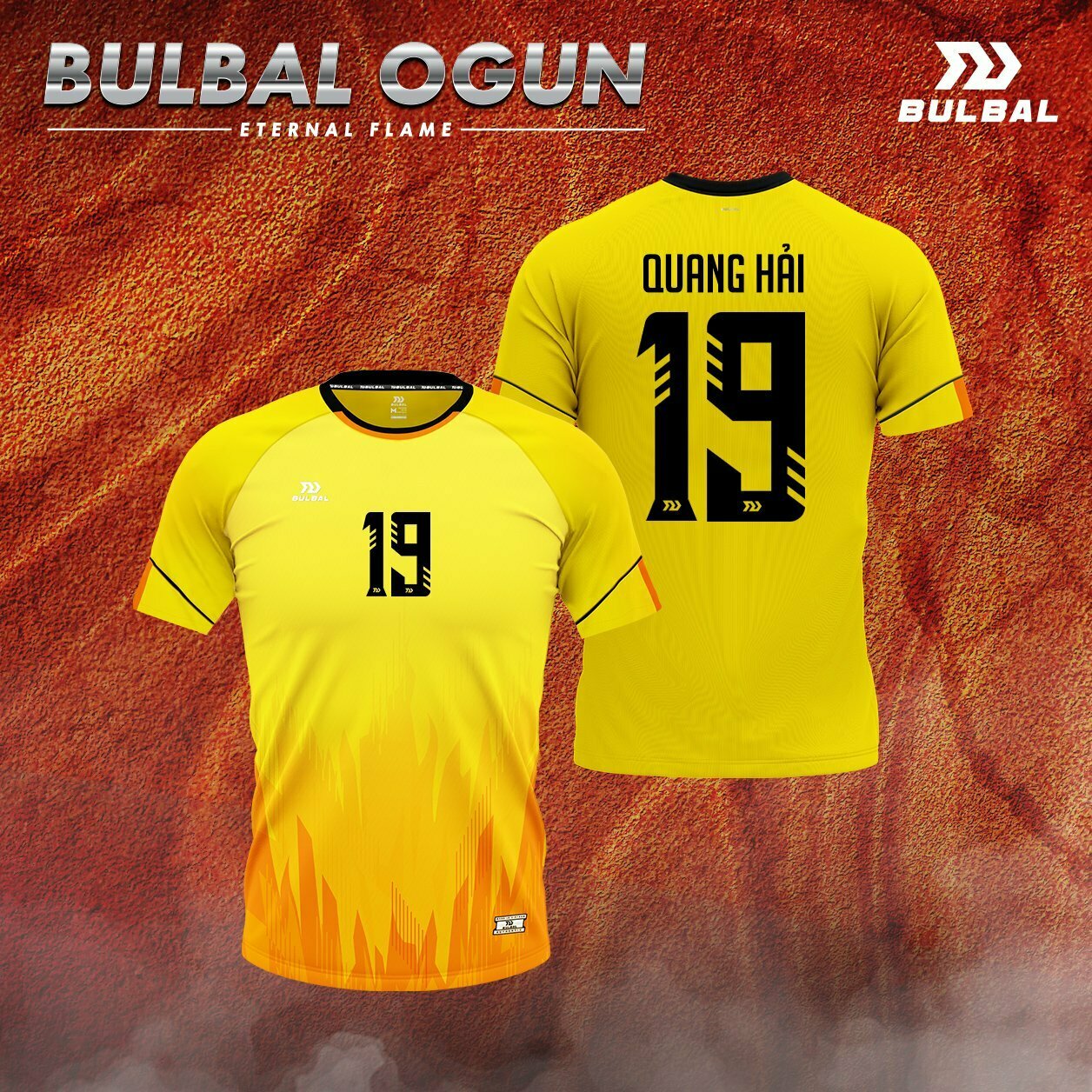
Font số áo bóng đá Bulbal Ogun
Mỗi một con số mang một ý nghĩa riêng trên sân đấu, thể hiện nhiệm vụ của từng cá nhân. Ngoài ra font số áo bóng đá đẹp giúp các VĐV tự tin thể hiện bản lĩnh trên sân cỏ.
Chính vì được sự quan tâm của nhiều khách hàng. Bên cạnh việc ra mắt BST quần áo bóng đá, Bulbal đã cho ra mắt bộ số font Bulbal Ogun. Lấy cảm hứng từ “ngọn lửa thiêng” thể hiện nghị lực mạnh mẽ chiến đấu hết mình. Màu sắc còn tượng trưng cho sự tinh khiết và tinh thần bất diệt.
Đây là font số áo bóng đá mới nhất 2022 tại nhà Bulbal. Được thiết kế kích cỡ đều đặn, đường nét độc đáo, khắc họa logo Bulbal ấn tượng. Sử dụng các đường cắt và góc cạnh sắc nhọn như một chiến binh đầy gai góc. Bộ font Ogun giúp các VĐV thể hiện tinh thần mạnh mẽ, sự quyết tâm bứt phá hết mình. Mẫu font số độc quyền thiết kế vô cùng đẹp mắt và đầy sáng tạo. Hy vọng có thể đem lại cho anh em sự yêu thích, lan tỏa nét riêng của bản thân.
Nếu đang tìm cho mình một font số áo đẹp chắc hẳn Bulbal Ogun sẽ không làm bạn thất vọng.
Bộ font Bulbal Ogun được thiết kế theo ký tự Tiếng Việt. Điều này giúp anh em dễ dàng và thuận tiện trong việc in ấn.